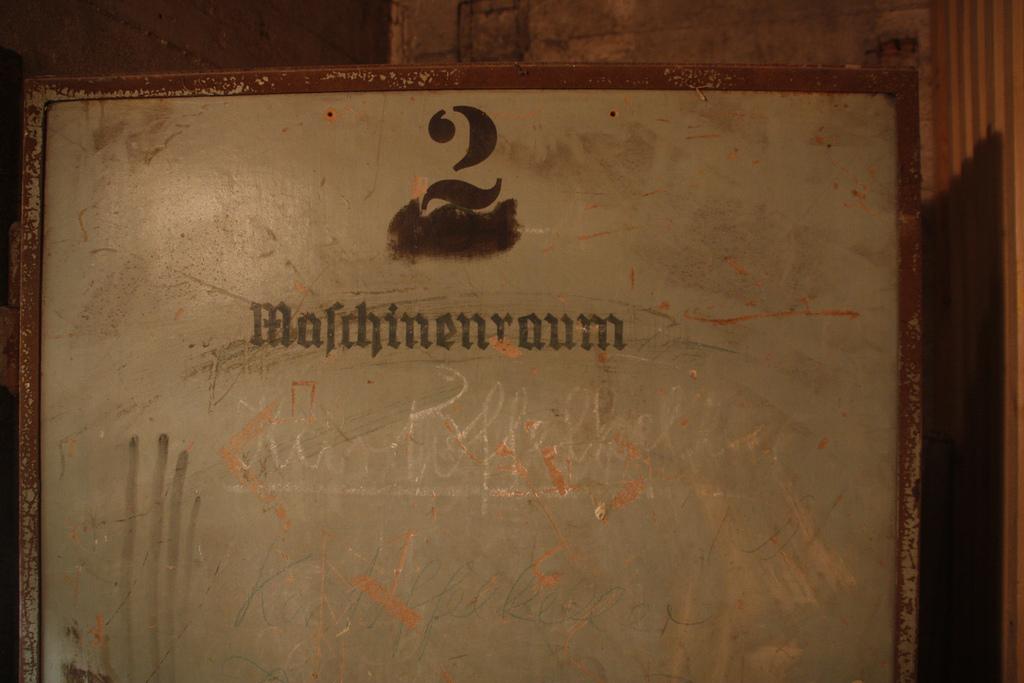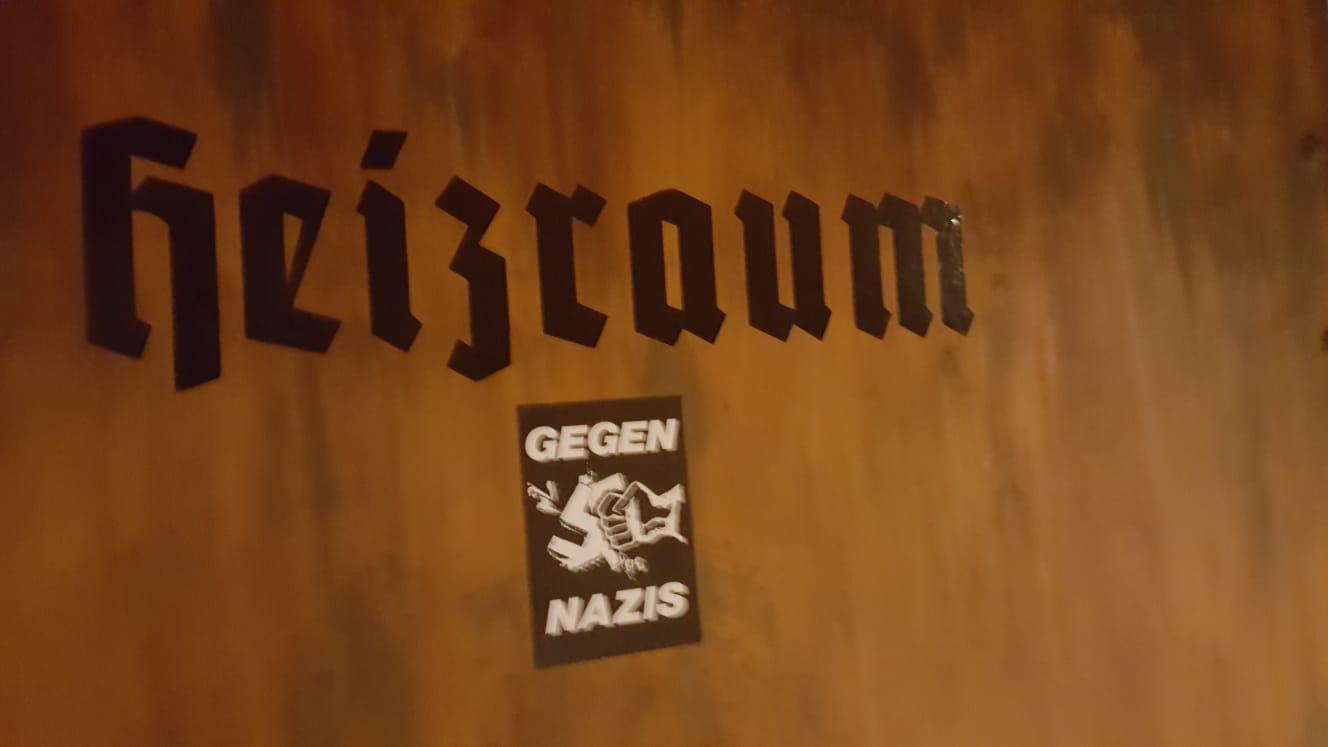
Hilfe bei Schriftarterkennung (Maschinenraum)
ich restauriere gerade eine alte Stahltür (nicht die im Bild) und verzweifle an der Schriftart des Aufdrucks. Ich bekomme einfach nicht raus welche Schriftart (speziell hinsichtlich des "M", "s", "h") das exakt - ähnliche "Schaftstiefelgrotesken" habe ich gefunden -  ist. Anbei ein Bild...
Ist halt – wie oft zu dieser Zeit – handgemalt. Klar, prinzipiell hätte das auch mit einer Schablone gemacht sein können, aber die doch recht unterschiedlichen As lassen mich doch eher vermuten, dass da, wie auch immer, keine Satzschrift direkt übernommen wurde. Also entweder hat dort jemand von Hand die Schablone entworfen oder eben gleich freihand gemalt.
Und stilistisch ist das eben so eine Übergangsschrift zwischen noch verspielteren Gebrochenen und den ganz strengen SSGs. Irgendwas in der Richtung gibt es bestimmt als heute verfügbare Digitalschrift. Wenn nicht heute, dann nächste Woche, von P.W. 🙂
Recht nah ran, wenn man bedenkt, das der Maschinenraum sehr wahrscheinlich Freihand gepinselt worden ist (das gehörte noch zur Maler-Ausbildung und ich habe als junger Mensch noch sehr ähnliche Schrift bei der Angabe des Schichtaufbaus an Stahlbrücken im Hafen gesehen,. ist des Herrn Helzels Potsdam schon recht nah dran.
Typeface:	Postdam
Designer:	Robert Golpon
Publisher:	Trennert und Sohn
Year:		1934
Digitalized by Manfred Klein in 2005
danke für die Hilfe, ich denke Potsdam ist tatsächlich am Nächsten dran, das "s"  baue ich mir aus dem "f" ;-)
das "s"  baue ich mir aus dem "f"
… oder aus der ſt-Ligatur, die im Zeichensatz enthalten ist.
Potsdam ist super. Erstaunlich wie schnell das in unserem Brettspielkeller gebrochen wurde...